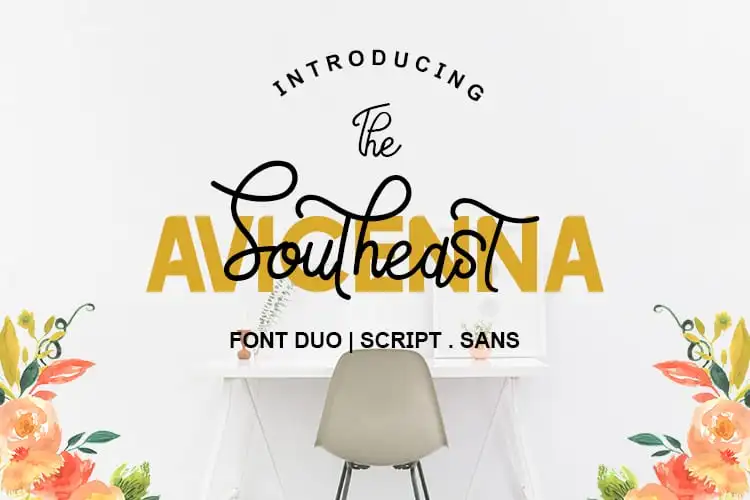
Southeast Font Duo – Download Grátis
Aqui está uma versão em português do Brasil das duas linhas curtos para a descrição da página de download da font ‘Southeast Font Duo’, categoria Script Fonts: Southeast é um duo de fóntes perfeito para se juntar às tuas criações digitais. Com seu touch natural e autêntico, o ‘Southeast’ traz uma aparência delicada e handwritten que te permite experimentar nuances sutis presentes nas escritas manuscritas reais. Ideal tanto para assinaturas quanto para cartões de visita ou revistas de negócios, este duo de fóntes também é ideal para uso em marcasurrounds, posts no blog, embalagens ou qualquer outro projeto que deseje um toque elegante e envolvente. Conectado a esse design único estão várias aplicações possíveis: cartões de boas-vindas, identidades corporativas, blogs, embalagens e produtos. Este duo de fóntes é uma ótima escolha para quem busca dar um toque pessoal em projetos digitais sem abrir mão da estética moderna e sofisticada. Acredito que esteja perfeito para tornar seus trabalhos mais atraentes, personalizados e únicos. Seja você um designer de moda, uma marca ou mesmo um blogueiro que pretende dar seu trabalho um aspecto mais autêntico e único – Southeast é a escolha certa.